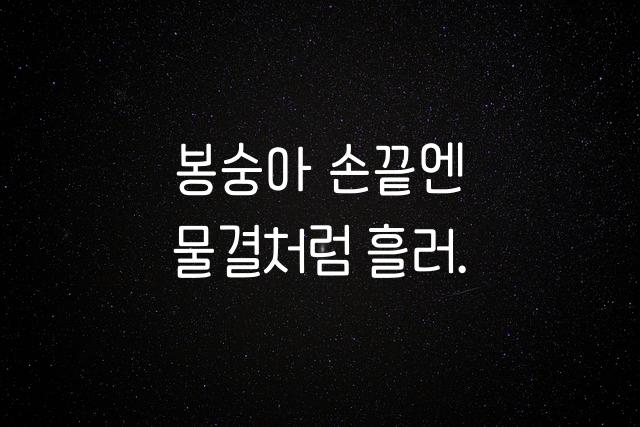
유토이미지고딕은 현대적인 감성을 담은 기본 고딕 폰트로, 굴림체의 세련된 변형을 제공합니다. 깔끔하고 명확한 라인이 특징이며, 일상과 전문적인 환경 어디에서나 활용도가 높습니다.
유토이미지고딕은(는)
기본 고딕, 감성적인, 부드러움 계열의 생김새를 가지고 있으며
웹/앱 디자인, 보고서/문서 등에서 자주 활용되며, 효과적인 메시지 전달에 적합합니다.
이 폰트는 기술/IT, 금융/비즈니스 분야에 잘 어울리며,
명확한, 단순한 느낌을 담고 있는 것이 특징입니다.